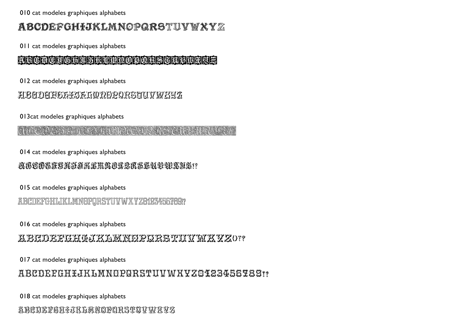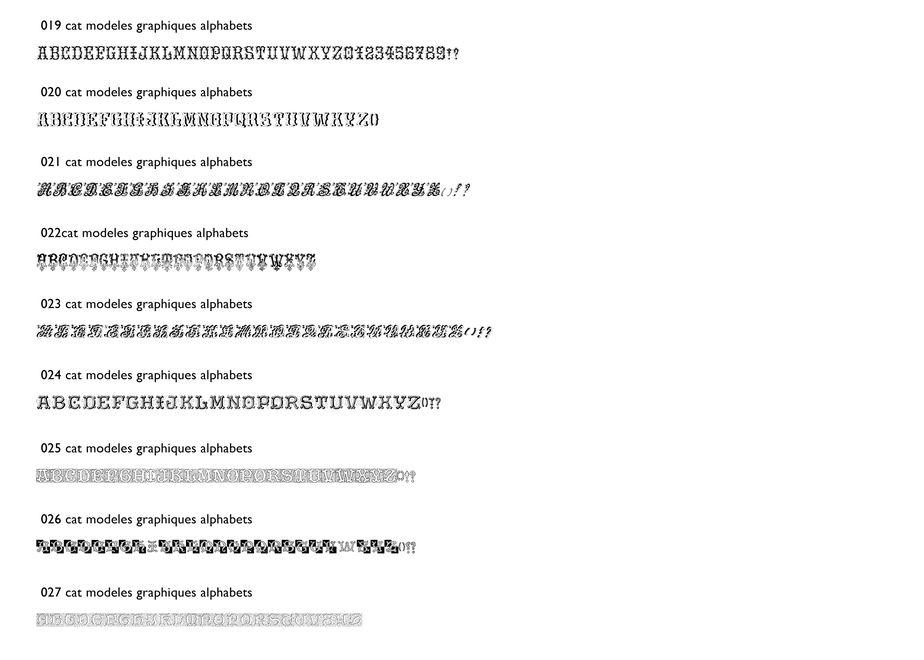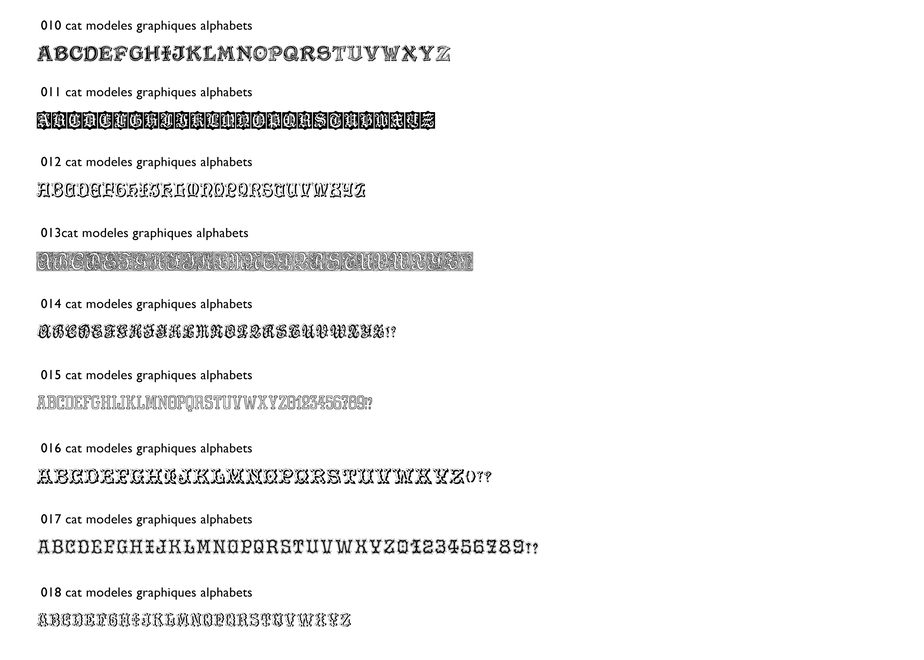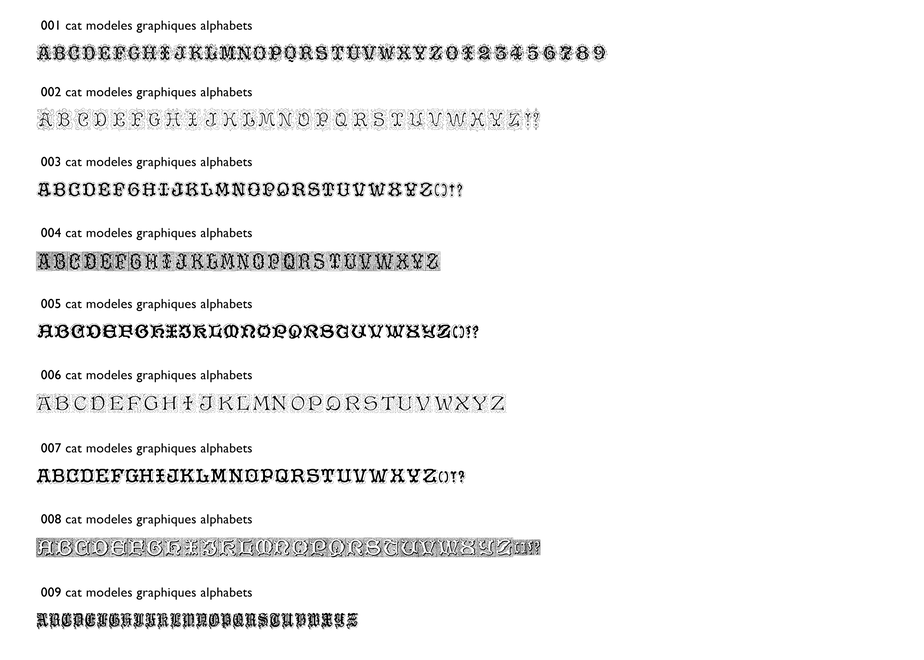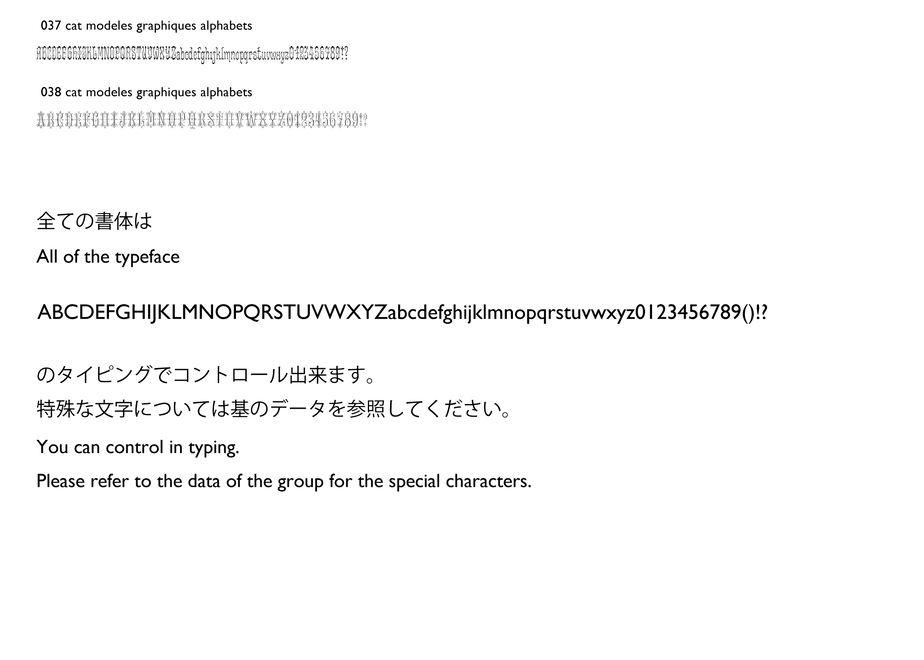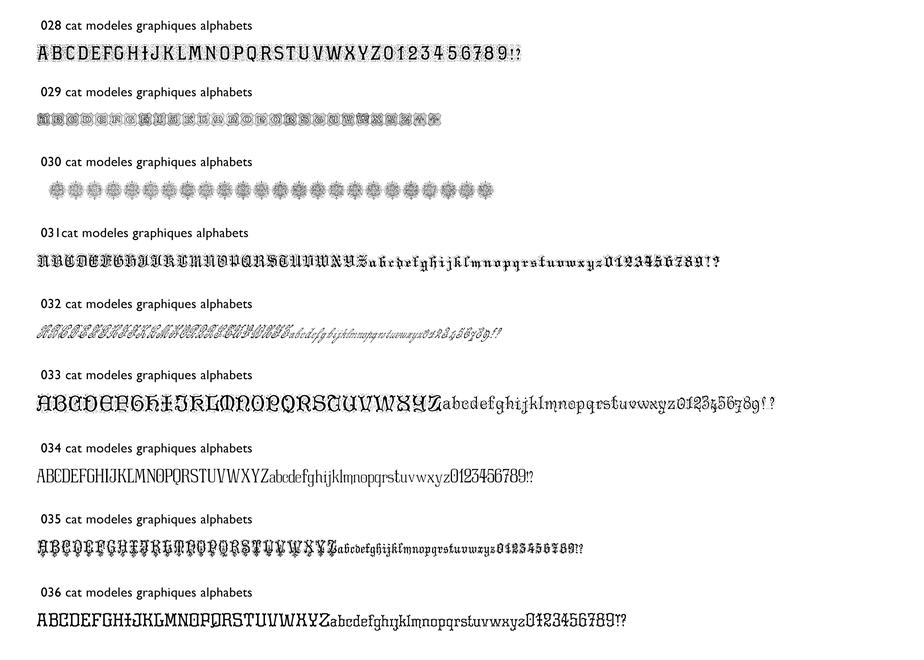
フォント:J. Laugier, Modèles graphiques d'alphabets industriels modernes
The decorative typeface sample book "J. Laugier, Modèles graphiques d'alphabets industriels modernes" has been changed from French to English and edited and excerpted into fonts. For special characters such as ligatures, the basic data is also recorded, so please use that.
Also, all fonts
"ABCDEFGHIJKLMNOPQRSTUVWXYZabcdefghijklmnopqrstuvwxyz0123456789 () !?"
You can control it by typing.
装飾書体見本帳「J. Laugier, Modèles graphiques d'alphabets industriels modernes」をフランス語仕様から英語仕様に変更し編集と抜粋したものをフォント化しております。合字など特殊な文字に関しましては基のデータも収録しておりますので、そちらを御利用ください。
また全てのフォントは
「ABCDEFGHIJKLMNOPQRSTUVWXYZabcdefghijklmnopqrstuvwxyz0123456789()!?」
のタイピングでコントロール出来ます。